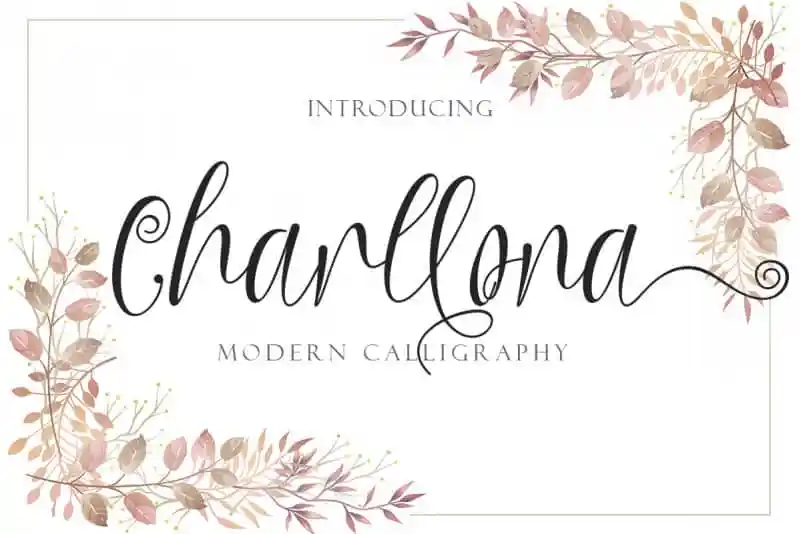
Charllona Calligraphy Font – Download Grátis
Charllona Calligraphy Font é uma fonte escrita que encanta com sua beleza única e versátil. Especialmente indicada para criações artísticas e casuais, a Charllona traz um toque especial aos seus trabalhos, seja em festas de casamento ou no seu negócio. Ideal tanto para criar cartões de convidados autênticos quanto para decorar seu hotel ou empresa, essa fonte oferece uma variedade de opções para tornar suas mensagens mais atraentes e memoráveis. Ainda mais interessante, esta fonte inclui elementos como swashes e ligaturas, proporcionando um toque refinado que adiciona uma personalidade única aos seus designs. Ela é perfeitamente adequada para anúncios promocionais, logotipos e identidades visuais, bem como materiais de mídia social, oferecendo o poder de expressar seu amor por texto ou frases memoráveis em qualquer projeto. Com sua riqueza de detalhes e design elegante, Charllona Calligraphy Font é a escolha perfeita para quem busca adicionar uma captação especial às suas criações. Esteja você criando um convite de casamento único, um logotipo sofisticado ou mesmo simplesmente querendo escrever algo romântico em seu feed do Instagram, essa fonte está aqui para tornar seus projetos mais lindos e memoráveis.